5 Fonts Menakjubkan Untuk Desain Web #1
Font adalah seni tipografi yang sangatlah penting bagi web desainer dalam membantu membangun website mereka, karena meskipun website itu cuman hanya dengan menampilkan desain hitam dan putih pada websitenya, asal layout itu tertata rapi dan ditambahkan font yang cocok maka akan menghasilkan desain yang meskipun sederhana tapi terlihat elegant. Jangan pernah menyepelekan Font dalam web desain anda. Berikut Centerklik akan memberikan 5 Font yang tentunya gratis tapi sangat bagus untuk membantu memperindah web anda.
1. Rosario
Rosario Fonts digambarkan oleh penerbit Omnibus sebagai semi-serif tipografi klasik, menampilkan kontras yang lemah dan ujung nampak halus. Font Sempurna untuk menetapkan jenis paragraf, Rosario ini ambil dari nama kota di mana desainer Héctor Gatti Lahir yaitu Rosario Argentina.
2. Roboto Slab
Roboto Slab merupakan salah satu Font varian dalam keluarga luas Roboto dirancang oleh Christian Robertson. Versi slab Font dengan bentuk geometris dan kurva terbuka. Ia terlihat menarik sebagai font untuk tampilan. irama letterform terasa alami, font ini membuat pembaca merasa nyaman.
3. Oswald
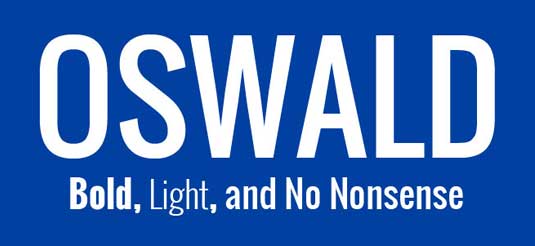
Salah satu font pertama yang akan tampil di library Web Font Google, Oswald telah diperbarui baru-baru ini untuk memasukkan beberapa bobot, karakter diperpanjang set dan kerning yang lebih baik. Font ini adalah pengerjaan ulang dari Alternate Gothic gaya sans-serif tipografi klasik, diciptakan oleh desainer Vernon Adams, dan merupakan tampilan font yang fantastis untuk judul dan keterangan.
4. Stalemate
Sebuah desain mengagumkan naskah kuno oleh Jim Lyles, dan sejarah kembali ke asal-usul vintage. Font ini bekerja dengan baik sebagai aksen atau tampilan font, gunakan tipografi ini untuk menambahkan kutipan “pribadi” Anda pada halaman website anda.
5. Crimson Text
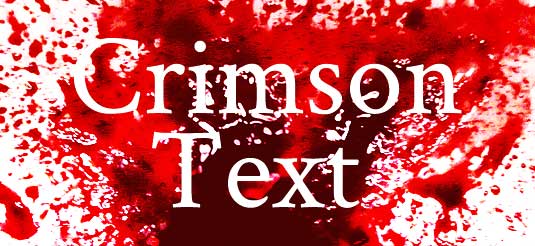
Font luar biasa dengan sentuhan halus ini jadikan sebagai pilihan yang baik. fot ini termasuk font serif yang terlihat baik dan proporsional. Dirancang oleh Sebastian Kosch dalam tradisi terbaik dari tipografi oldstyle seperti Garamond, fitur ini ordinals bentuk huruf, yang indah diberikan menjadikannya pilihan yang solid dan handal untuk banyak aplikasi.